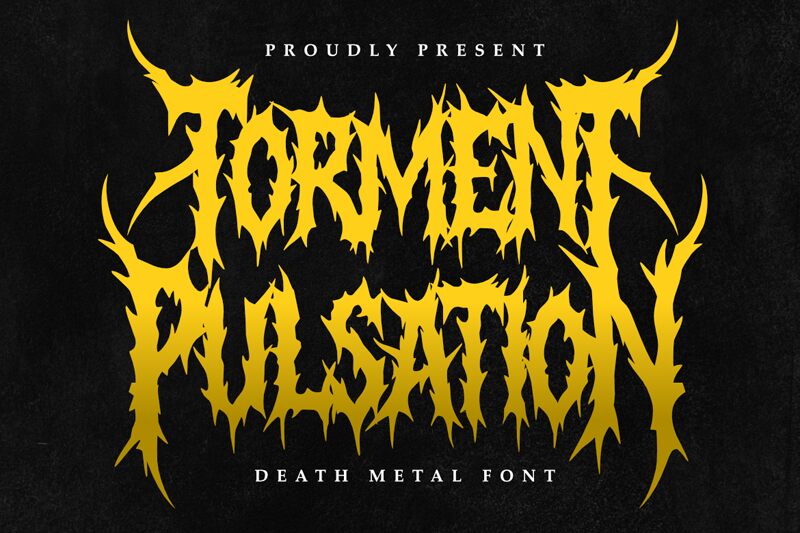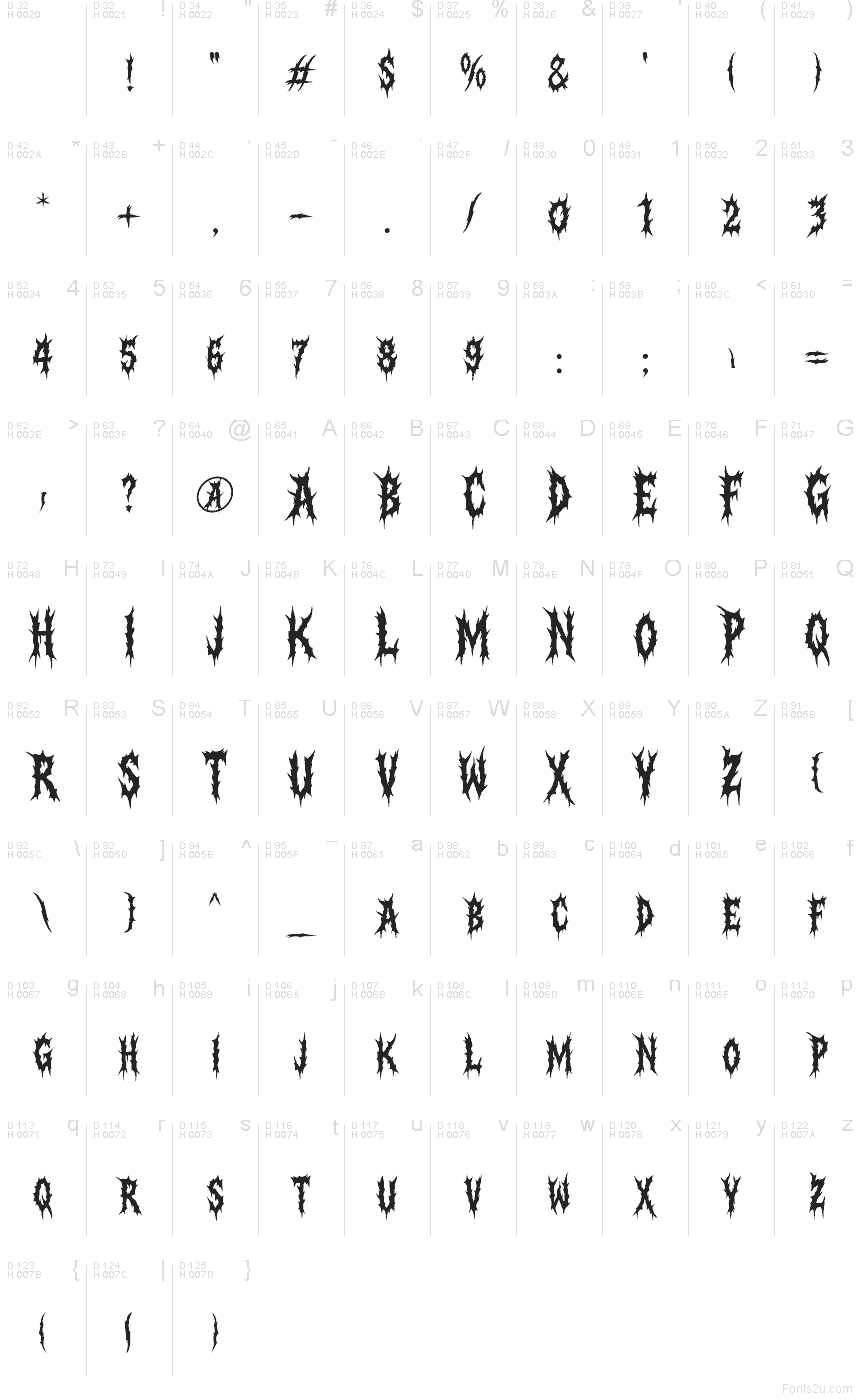
Torment Pulsation Regular
Torment Pulsation, créée par Masyafi Studio, est une police gothique gratuite aux traits acérés en forme d'épines. Ses bords tranchants confèrent à chaque lettre un rythme distordu et inquiétant. Les formes semblent sculptées et torturées plutôt que dessinées, avec des pointes irrégulières et des interstices acérés qui maintiennent une tension palpable d'un caractère à l'autre.
Torment Pulsation est idéale pour les affiches de films d'horreur, les logos de groupes de métal, les titres de jeux vidéo, les flyers pour Halloween, les visuels d'événements sombres et le merchandising gothique. Sa silhouette brisée impose une esthétique brute et troublante dans les textes courts. Cette police gratuite convient également parfaitement aux pochettes d'albums, aux étiquettes d'avertissement et aux visuels percutants sur les réseaux sociaux, là où vous souhaitez un lettrage à l'aspect fracturé et tranchant.